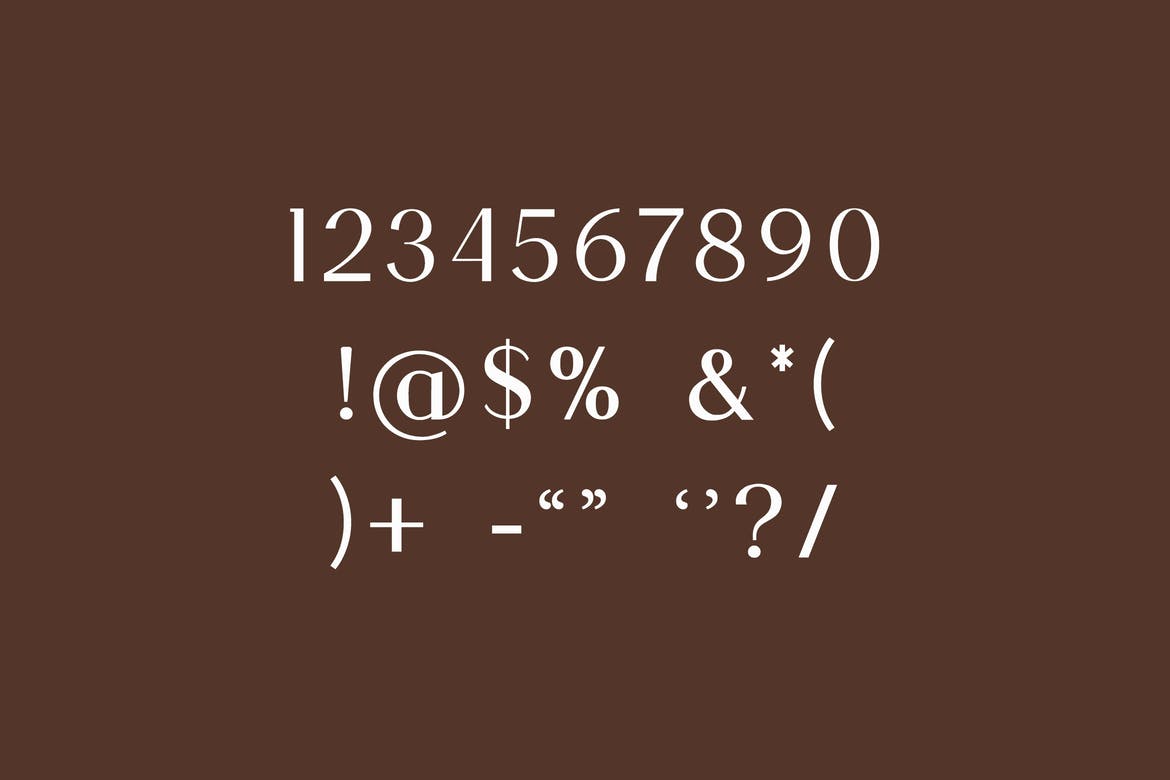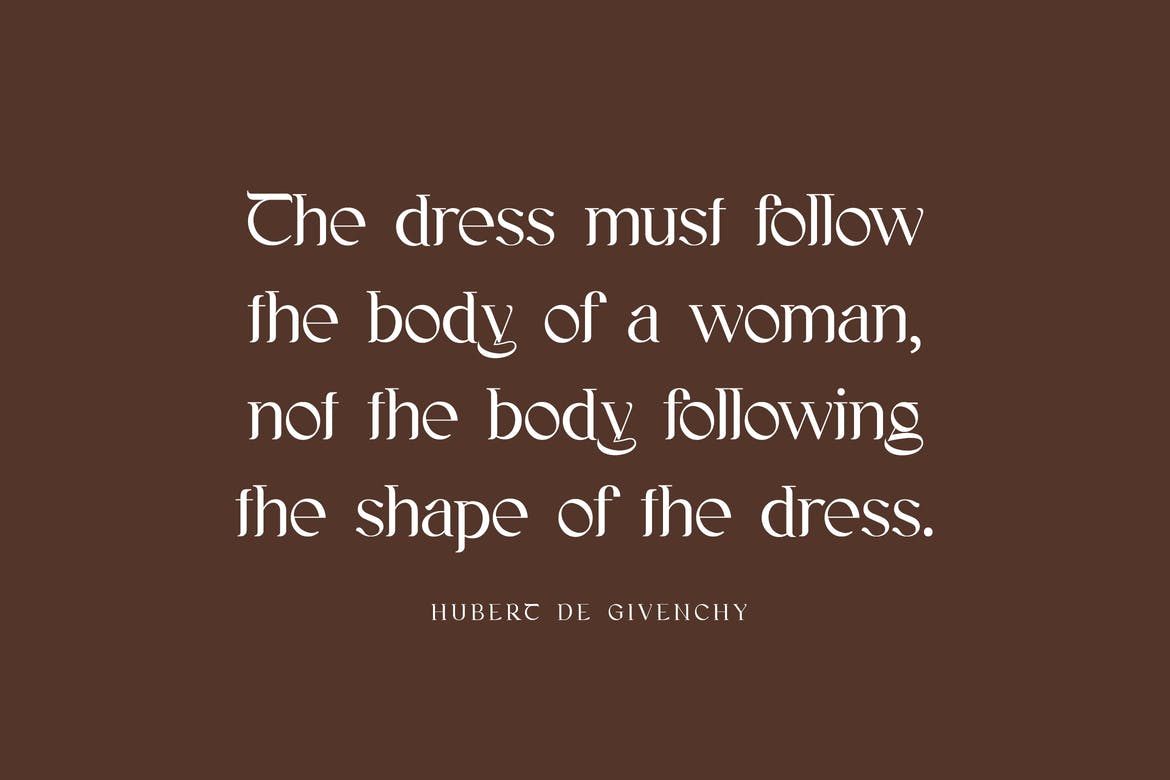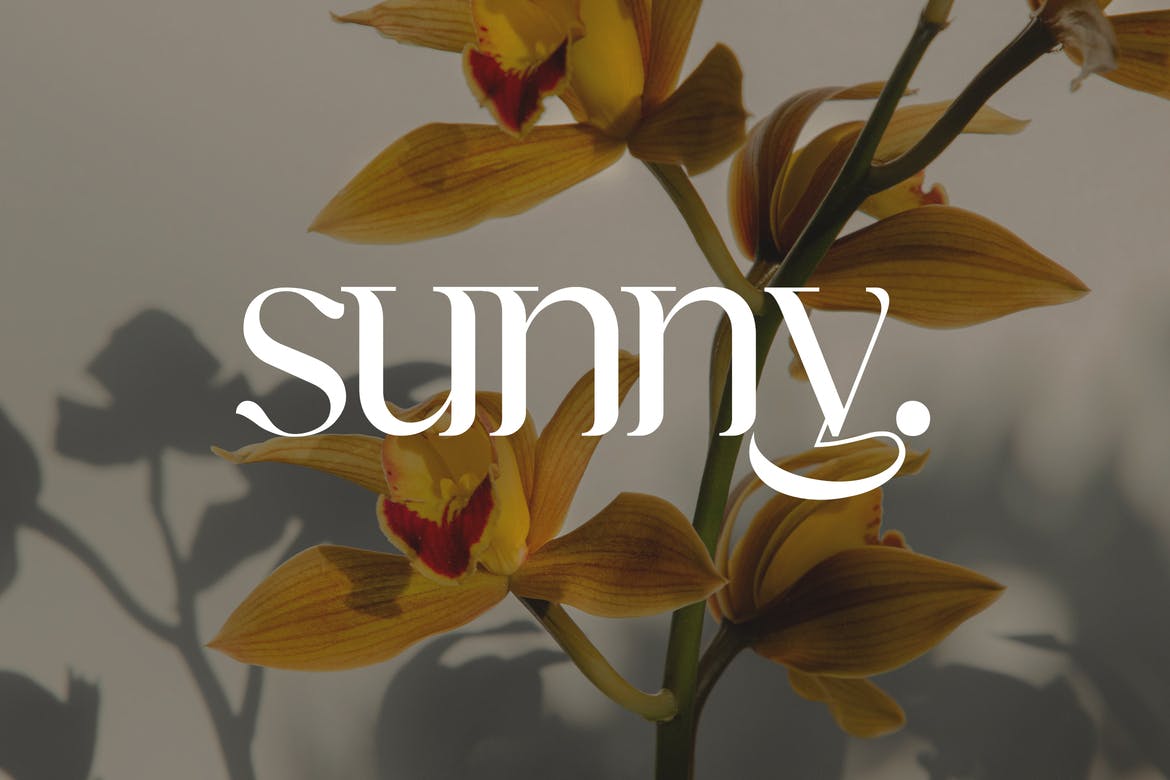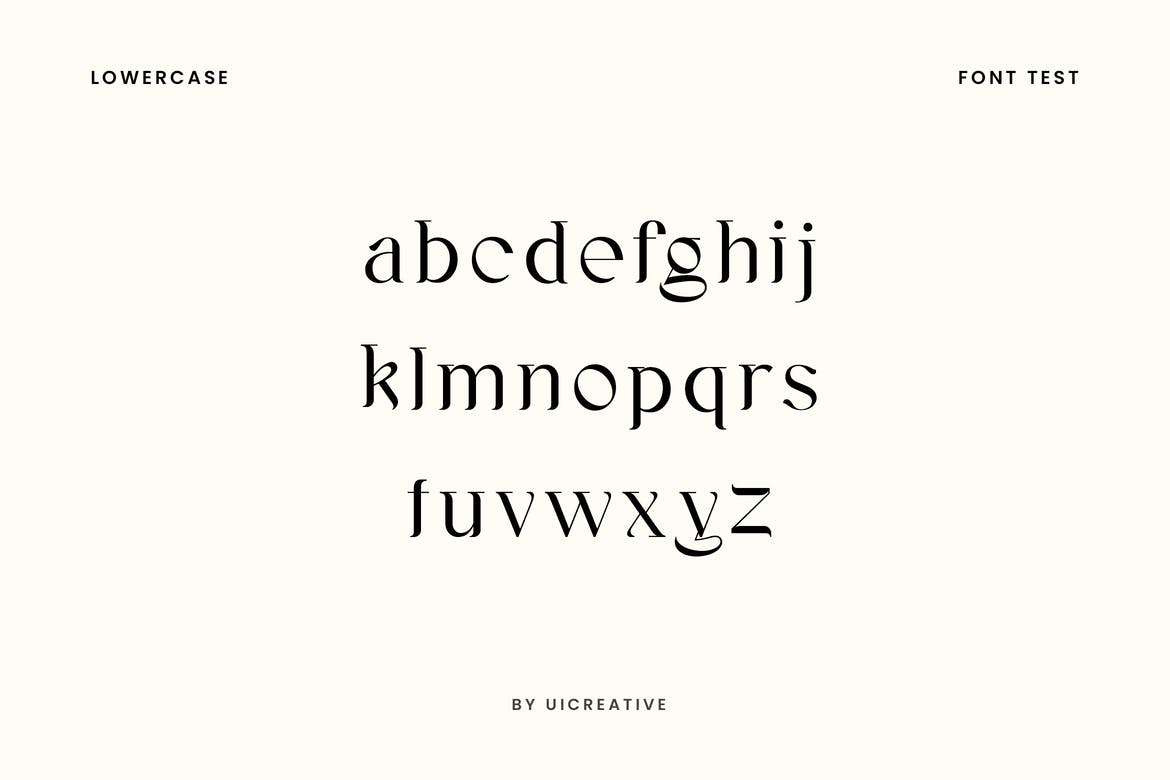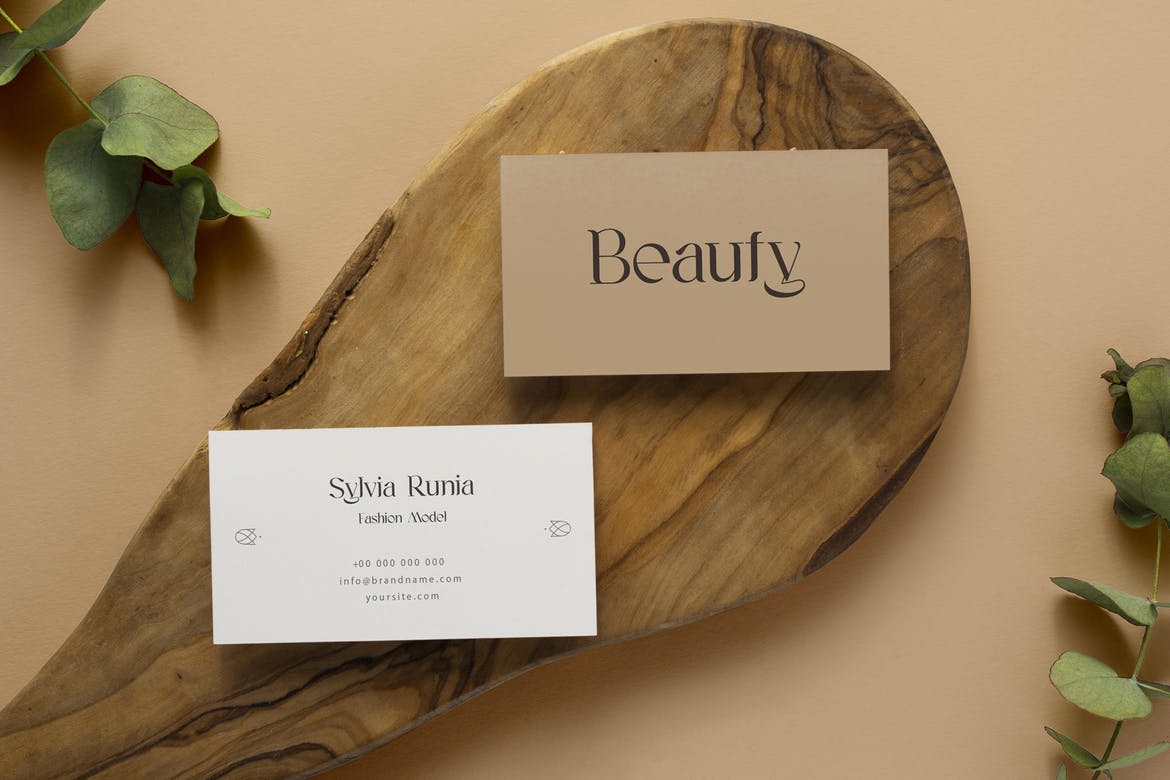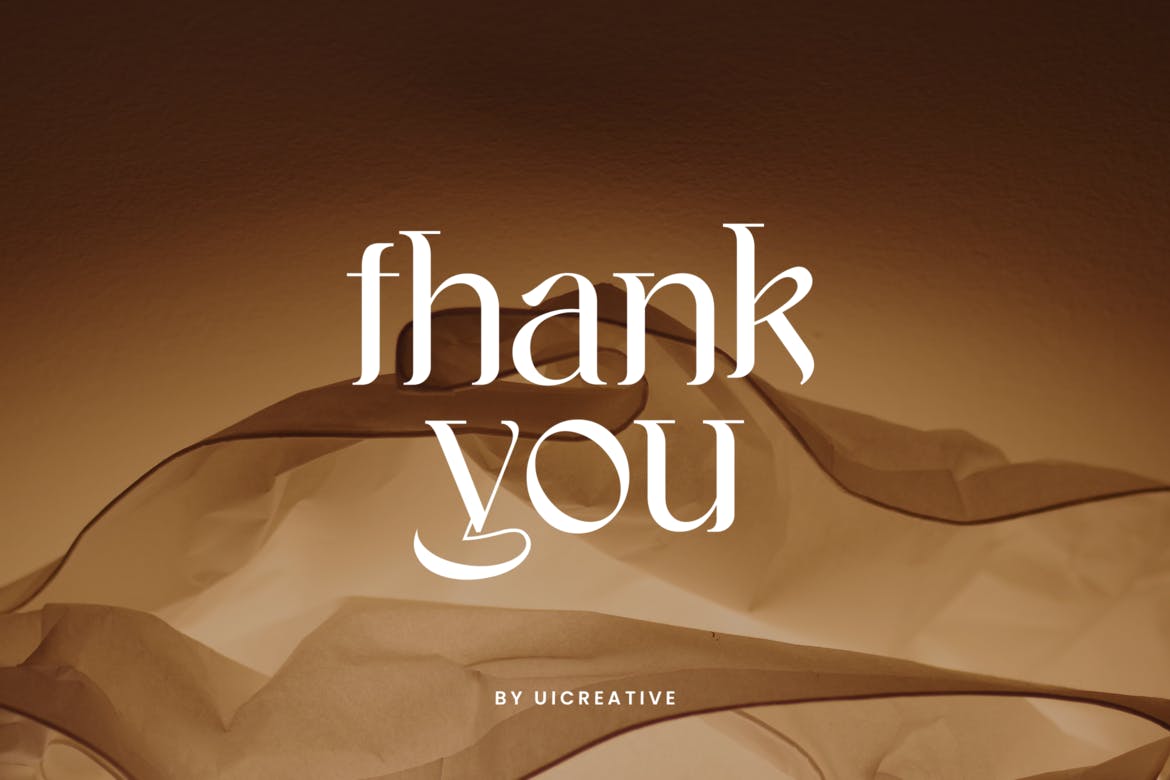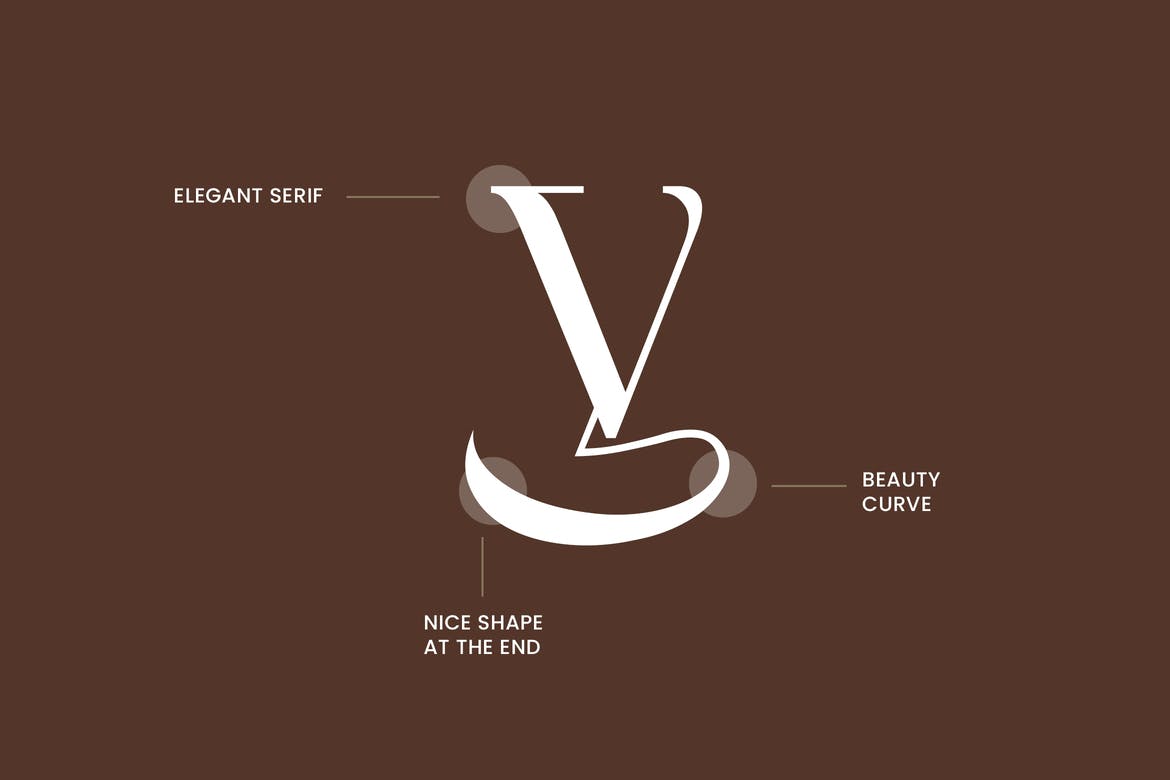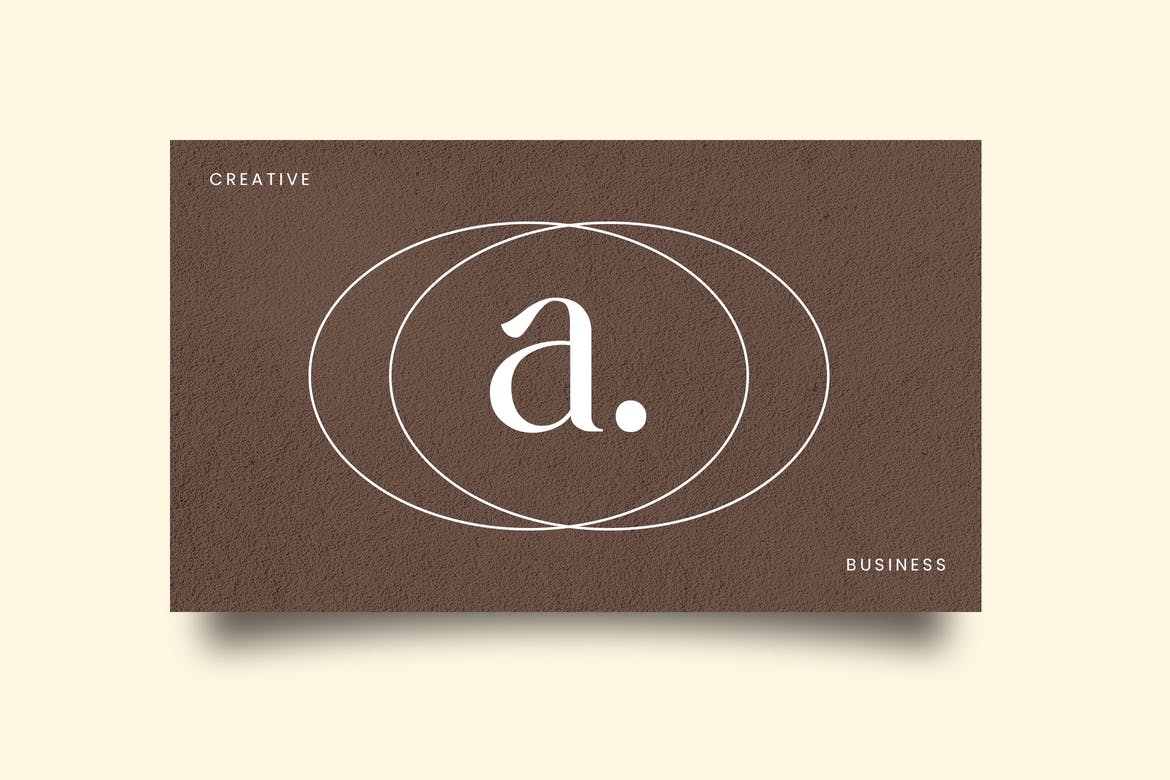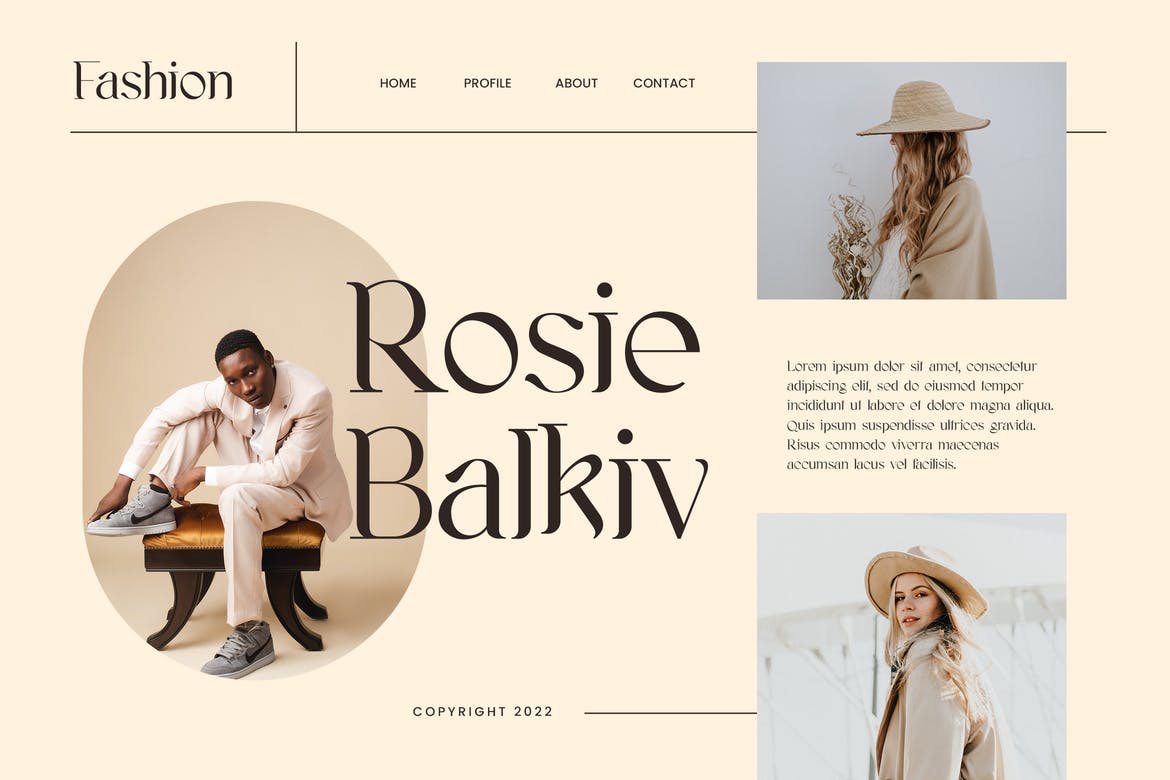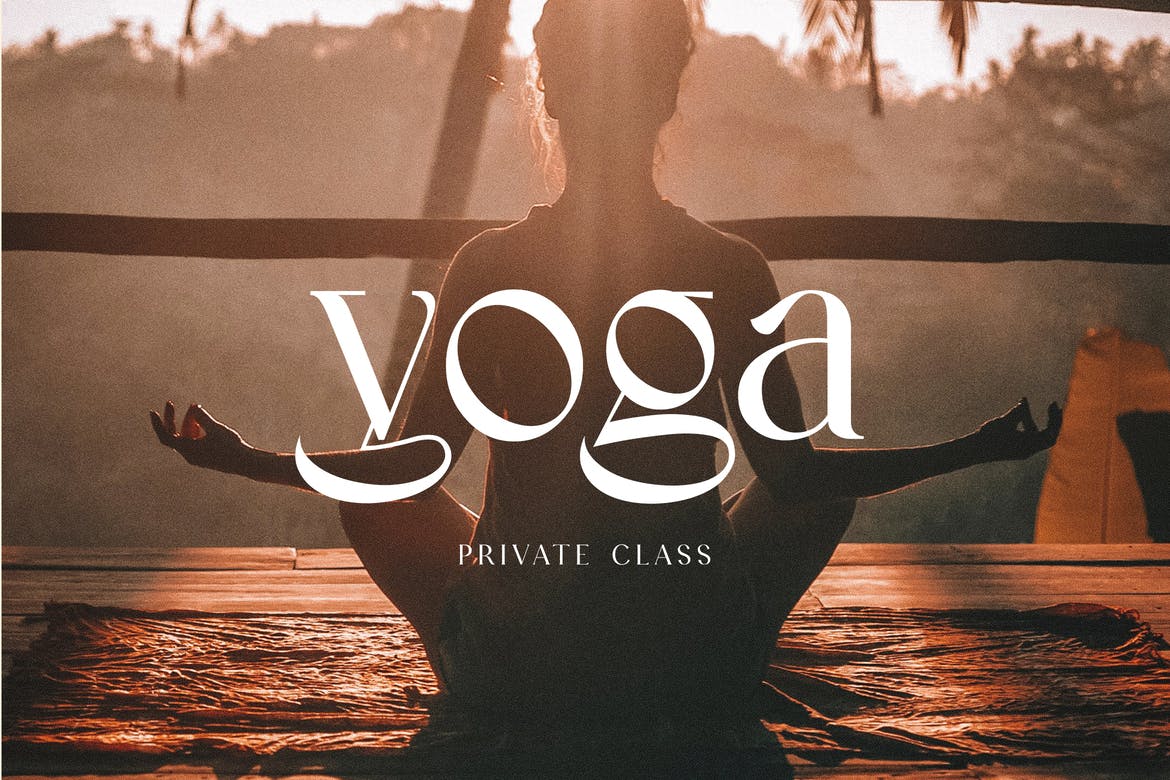
Aishwarya Luxury Serif Font
فونت Aishwarya Luxury Serif، انتخابی ایده‌آل برای پروژه‌های طراحی شما.
ما به شما فونت Aishwarya Luxury Serif را معرفی می‌کنیم. این فونت مدرن و سریف، احساسی زیبا، کلاسیک و مدرن دارد که آن را به گزینه‌ای بی‌نظیر برای پروژه‌های مختلف تبدیل می‌کند. این فونت به‌خوبی برای امضا، لوازم‌التحریر، لوگو، مراسم عروسی، نقل قول‌های تایپوگرافی، جلد مجله یا کتاب، هدر وبسایت، پوشاک، برندسازی، طراحی بسته‌بندی و موارد دیگر مناسب است. همچنین، طراحی‌های برندسازی مرتبط با مد یا طراحی‌های ویرایشی، هر دو ویژگی‌های مردانه و زنانه را به نمایش می‌گذارند.